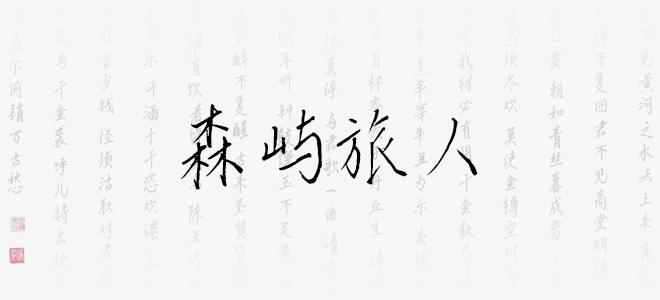
森嶼旅人是偏書(shū)法感的手寫(xiě)體。該字體行筆流暢,粗細(xì)拿捏到位,適當(dāng)?shù)倪B筆更增添了行書(shū)應(yīng)有的瀟灑。適用于文藝類的書(shū)刊、品牌廣告和產(chǎn)品包裝設(shè)計(jì),以及社交網(wǎng)絡(luò)的個(gè)性化用字。
森嶼旅人